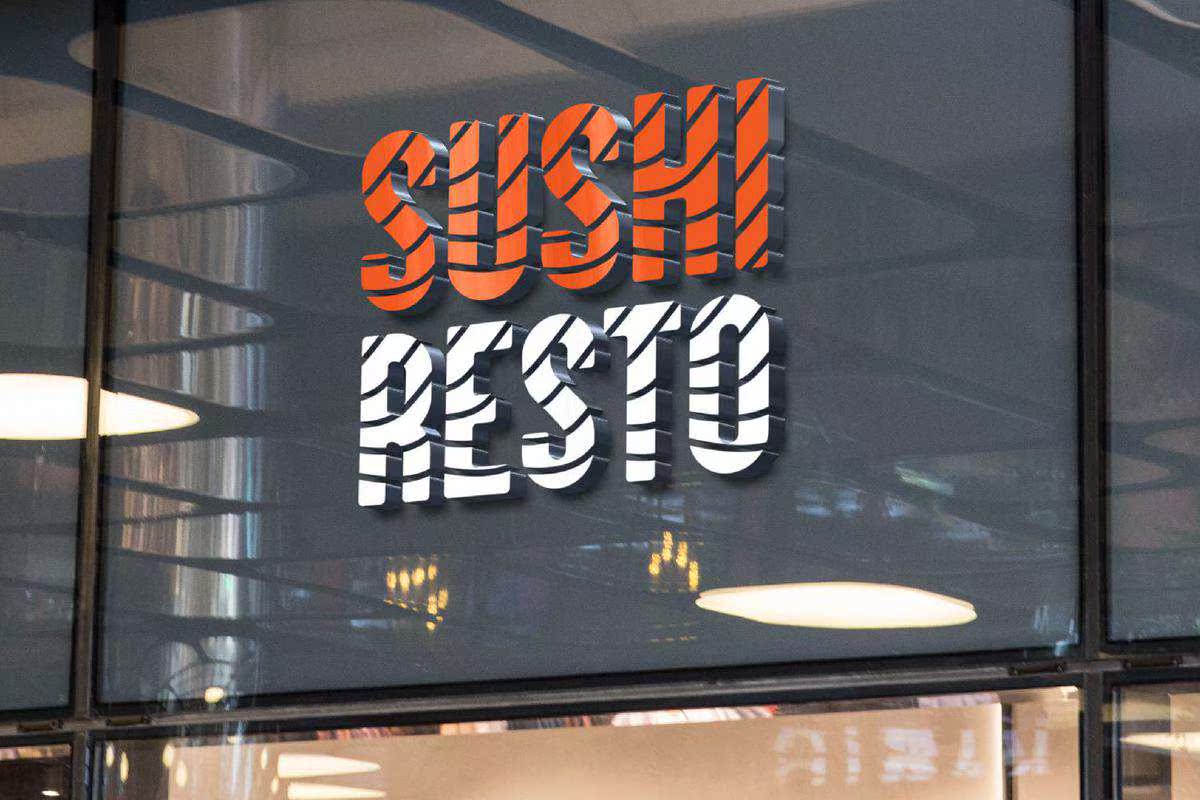
Salmoon是一种全新的字体,带有Almon-Meat纹理,并带有Anjapanese Food、Asian和Ientallooks,是我们具有Ananasian生态位的创意项目、标题标题、电影海报、quotestext的完美公司,因此Salmoon是一种全新的字体,带有Almonese纹理,并带有Anjapanese Food、Asian和Ientallooks,是我们具有Ananasian生态位的创意项目的完美公司,标题、电影海报、引文等等